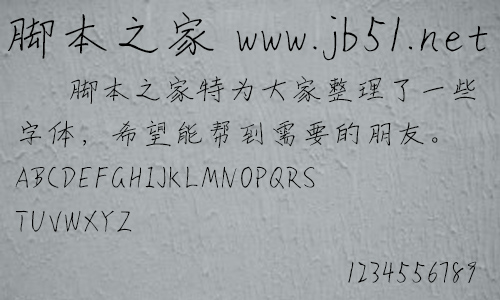
漢儀任嘉倫簡體是由漢儀字庫出品的藝術(shù)字體,這款字體筆觸較為纖細(xì),字體書寫端正大氣,具有很好的視覺感,適合應(yīng)用于藝術(shù)設(shè)計(jì)、平面宣傳設(shè)計(jì)、網(wǎng)頁設(shè)計(jì),書法字帖等領(lǐng)域。需要的朋友快來本站下載使用吧!